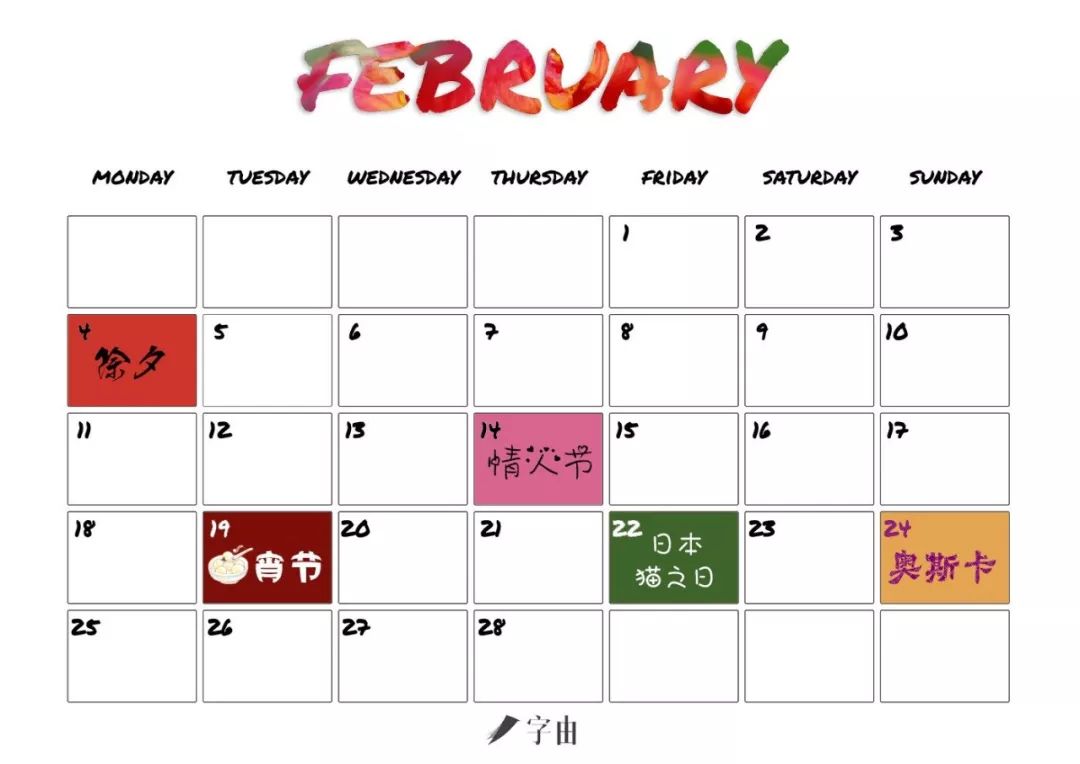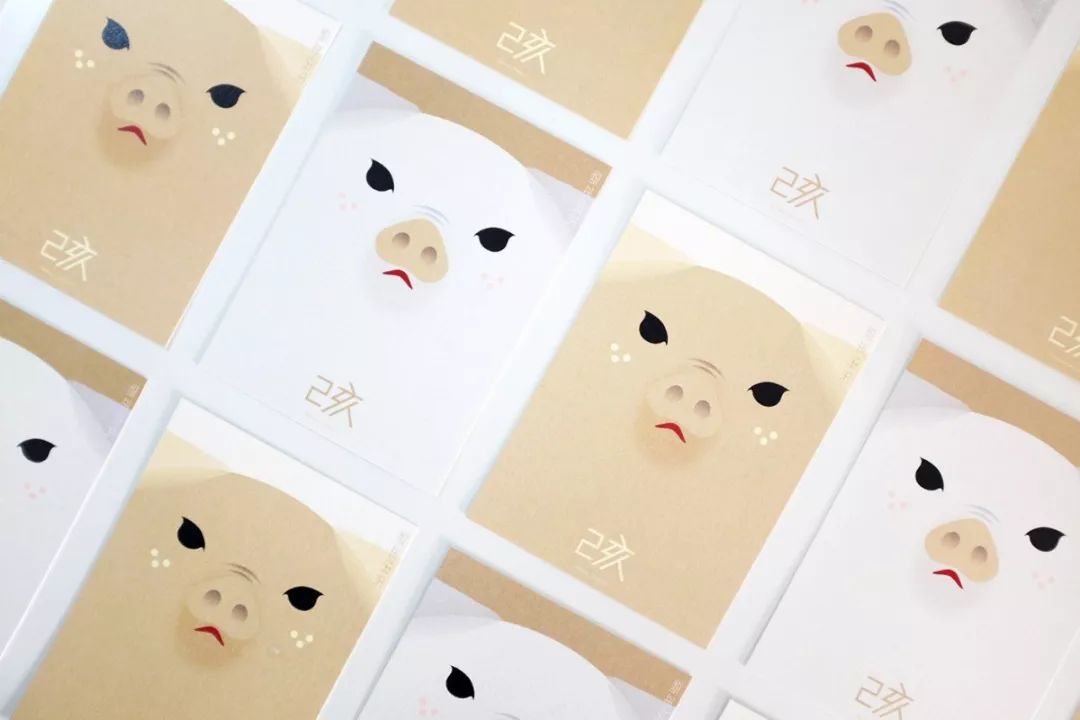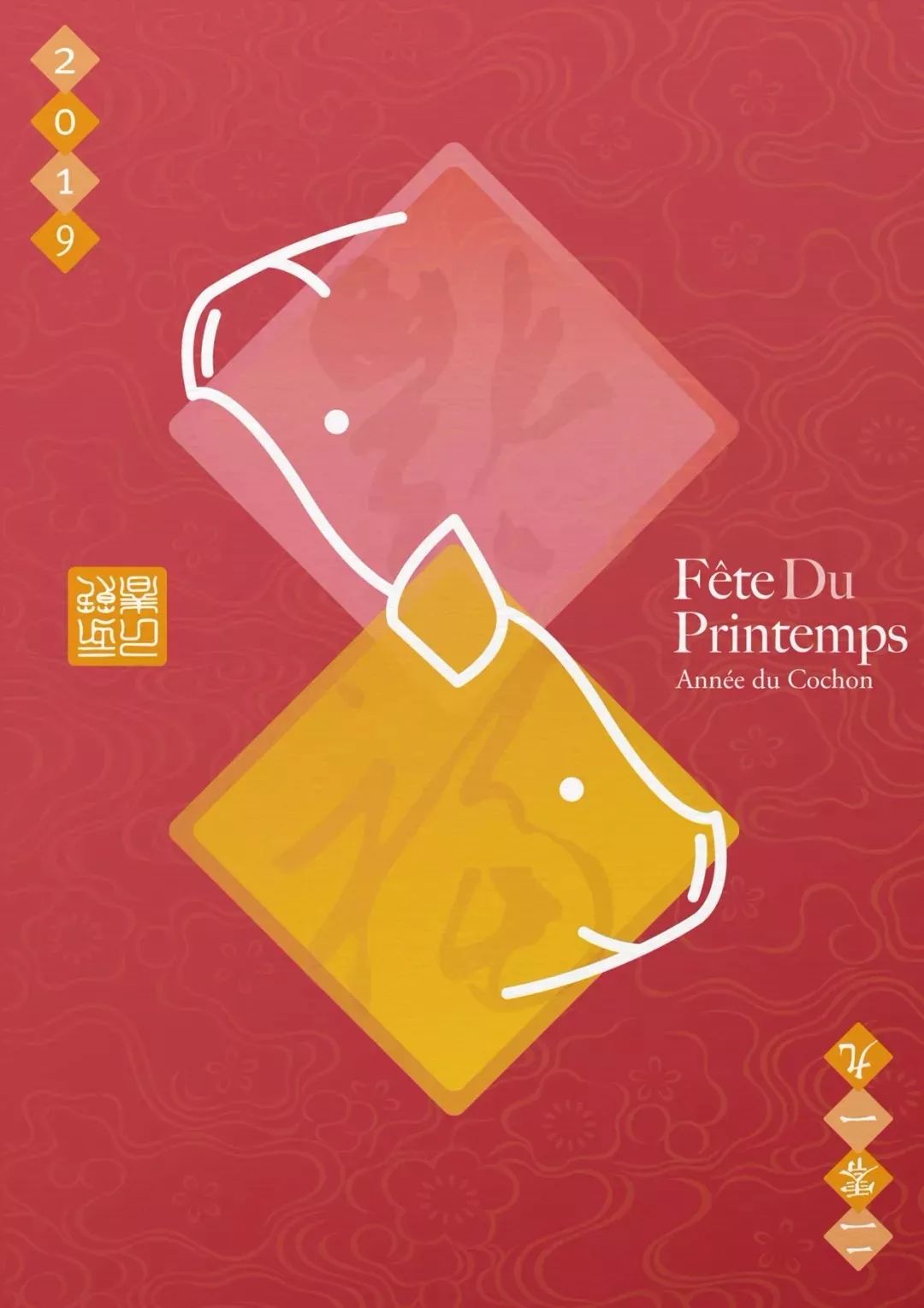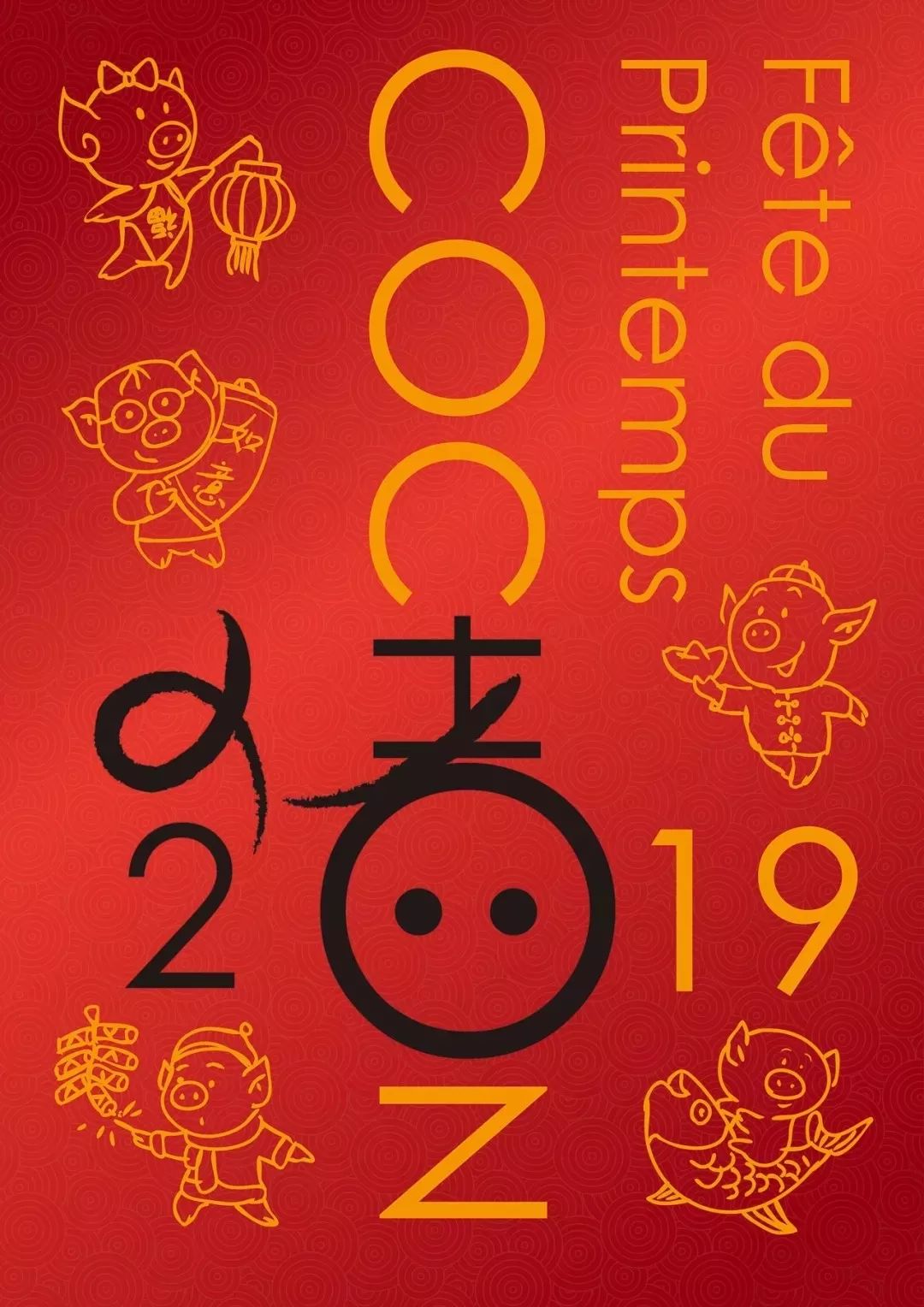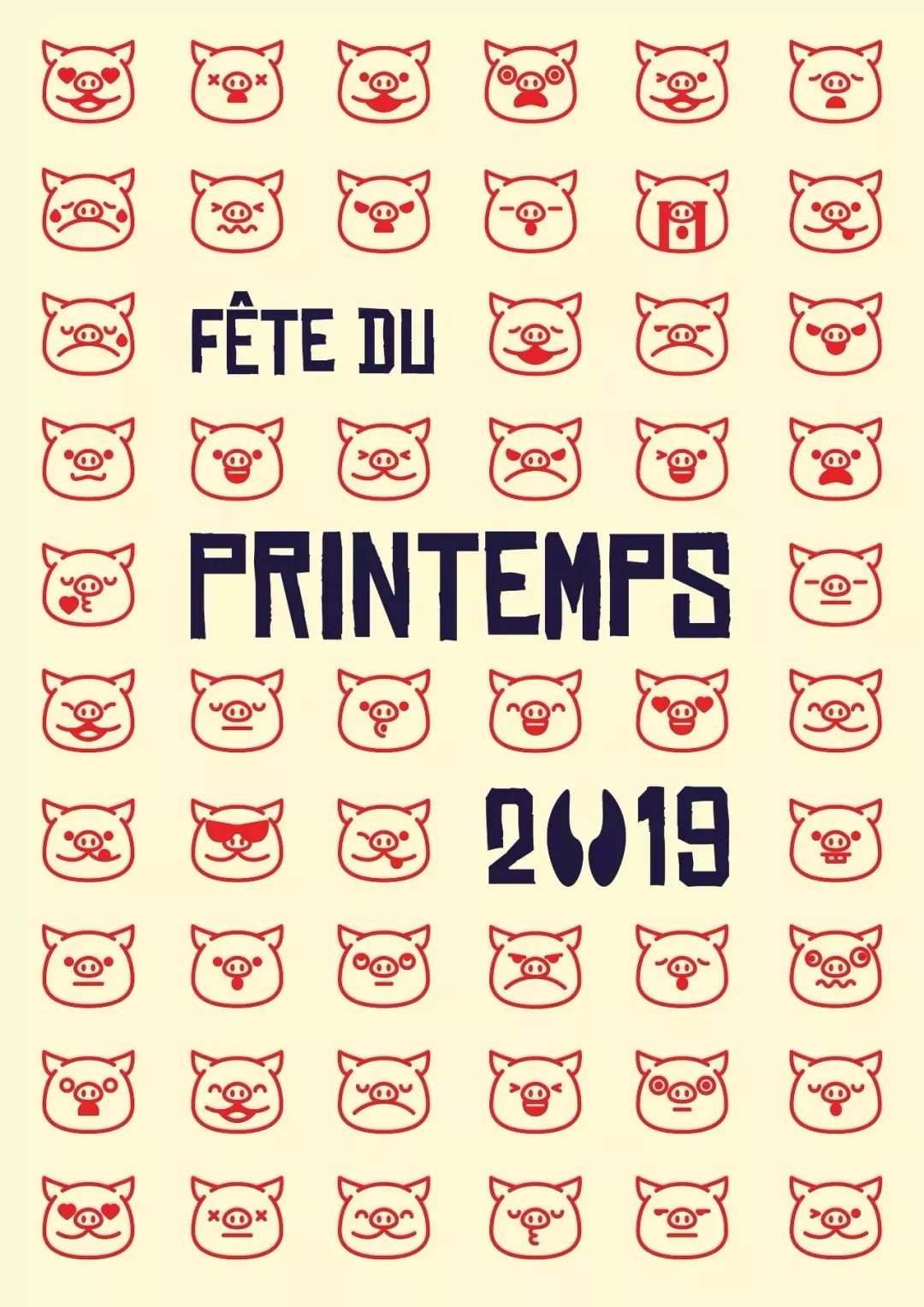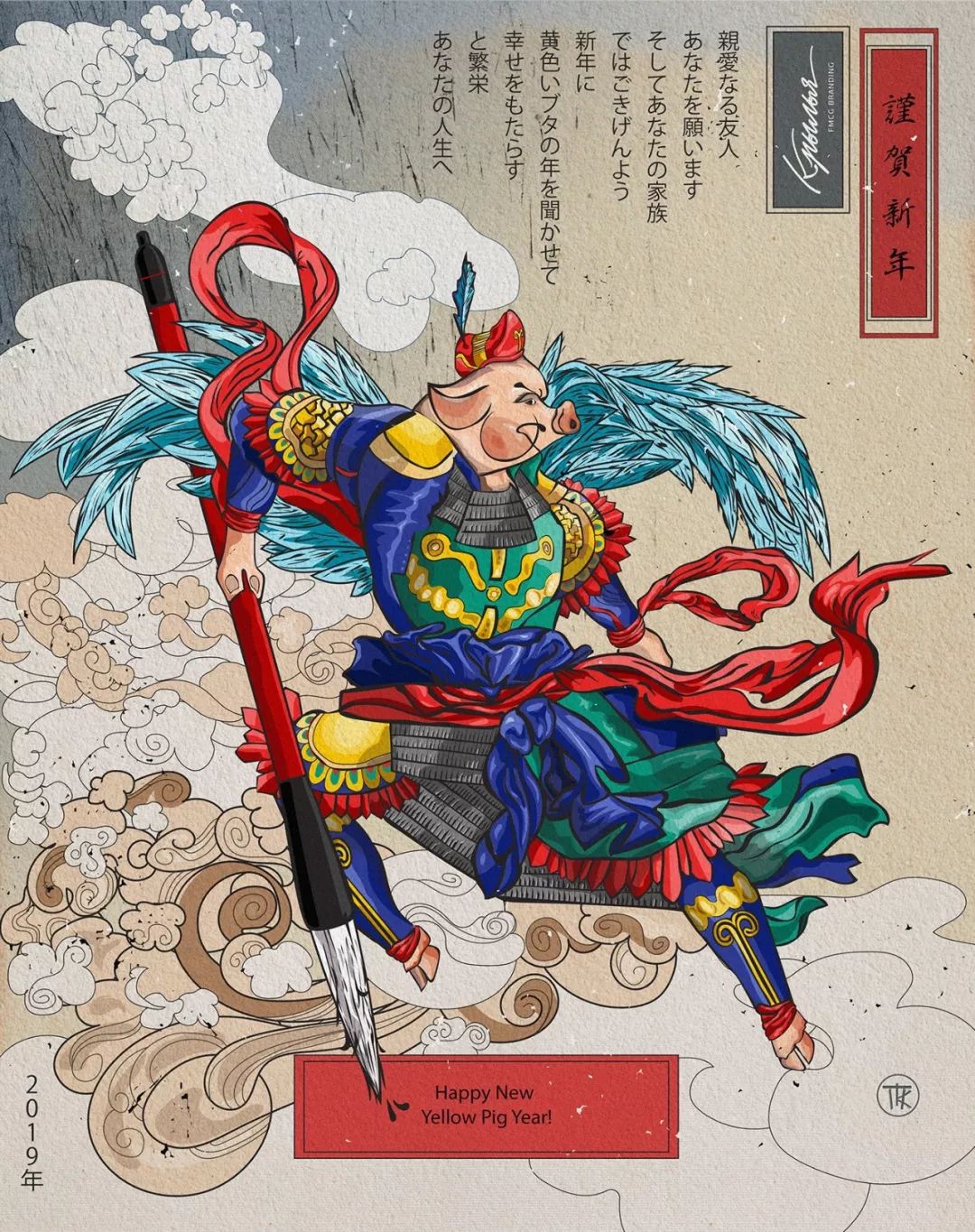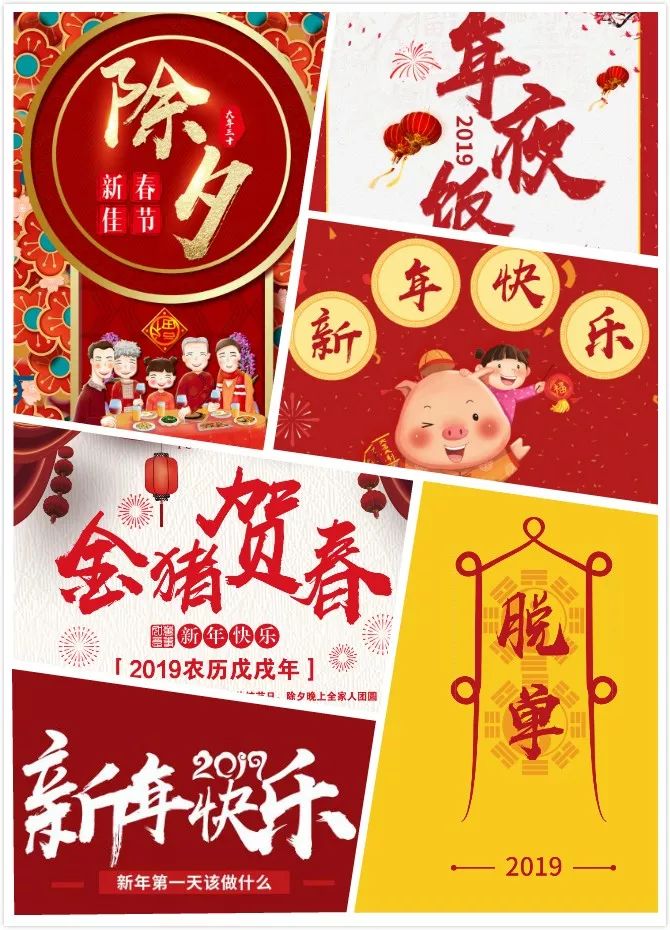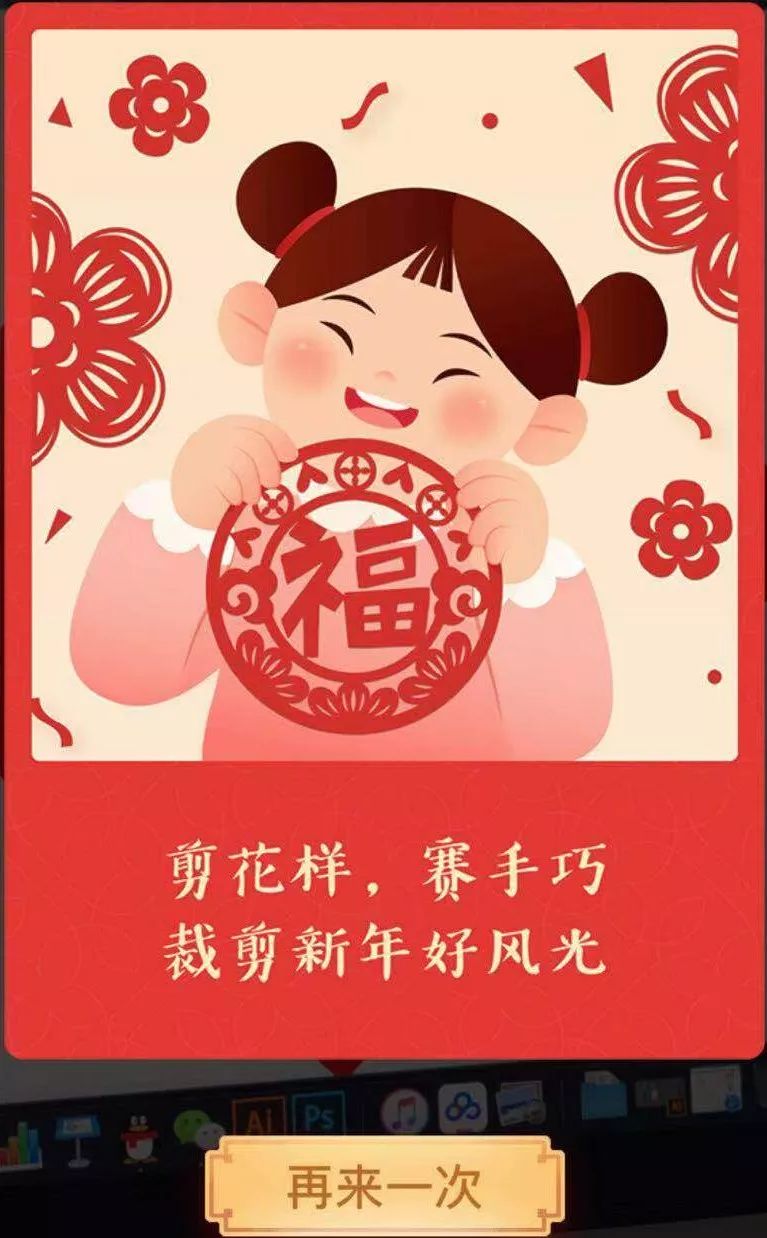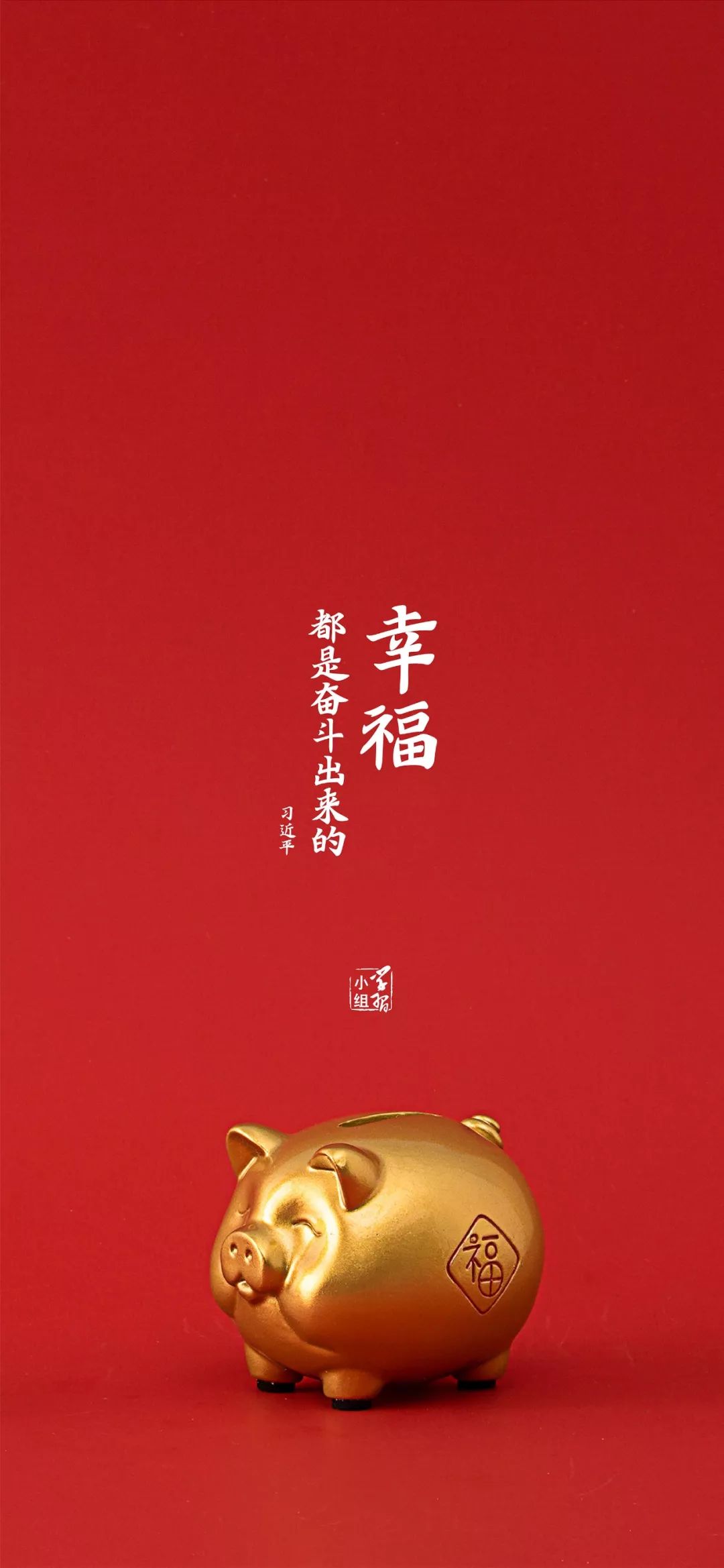
Behance上的设计再香,也没这些设计案例有年味~
2月第一天,你需要这个,贴心不?
今天柚子想说说东西方理念上的差异,看图:
这是怕贺岁档喜剧片太多,强行用惊悚片吸引视线嘛?prada、Burberry,你们太有心机了,不过注定被群嘲……
看看人家,还知道加个红红火火的背景。
也知道顺应属相,整各种小猪佩奇~
呃,这个猪有点凶,知道己亥了不起啊!
再给你加个福,变化一下汉字,有创意吧~
嗯,就是不够热闹,那就繁衍……
没有跟传统结合,那就化身天蓬元帅……
不想看猪了,行不行?可以啊,看夜景……
一口老血喷出,总觉得哪里不对,又说不出什么不好……
其实就是差一个很重要的年味,比如我们泱泱大国的人气。
还有合家团圆的气氛。
再加上各种逛庙会、打麻将、放鞭炮等传统项目,才有意思。
而这些,想让歪果仁理解,确实是不太容易。最明显就是打开behance,春节是这样~
而国内某网站是这样,间距都不一样发现没,除了红还是红,土是土了点吧,但这就是过年的taste~
所以说,咱自己的中国年,要自己来设计,不是还有我们嘛,走着~
上次柚子总结的字体界的C位之争,简直比春运还要热闹,这次也有,首先就是汉仪尚巍手书:
其次就是汉仪铸字童年体(左)、汉仪铸字木头人(右),表现很抢眼~
还有集五福很火爆的汉仪新蒂唐朝体,我在公交车上都看见它了~
还有汉仪趣黑、汉仪小麦体、汉仪喵魂自由体、汉仪星球体、汉仪雅酷黑、汉仪黑荔枝体,你都很熟悉了。
怎么没有汉仪北魏写经?这不嘛,配上励志语录,直接当手机壁纸~
也有新鲜出炉的汉仪颜楷、汉仪古隶,感觉很适合春节呢~